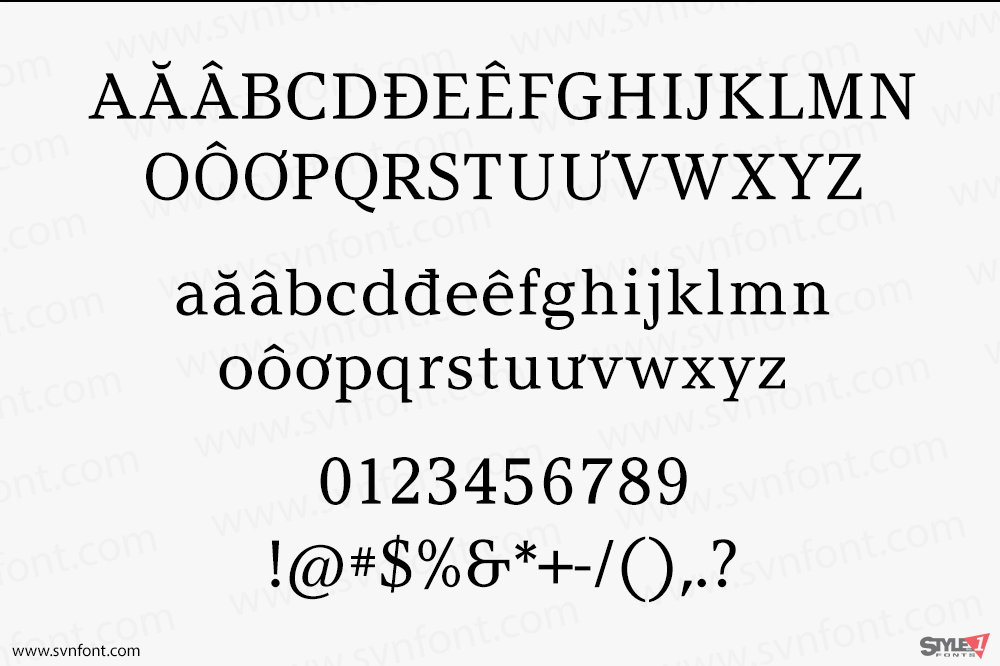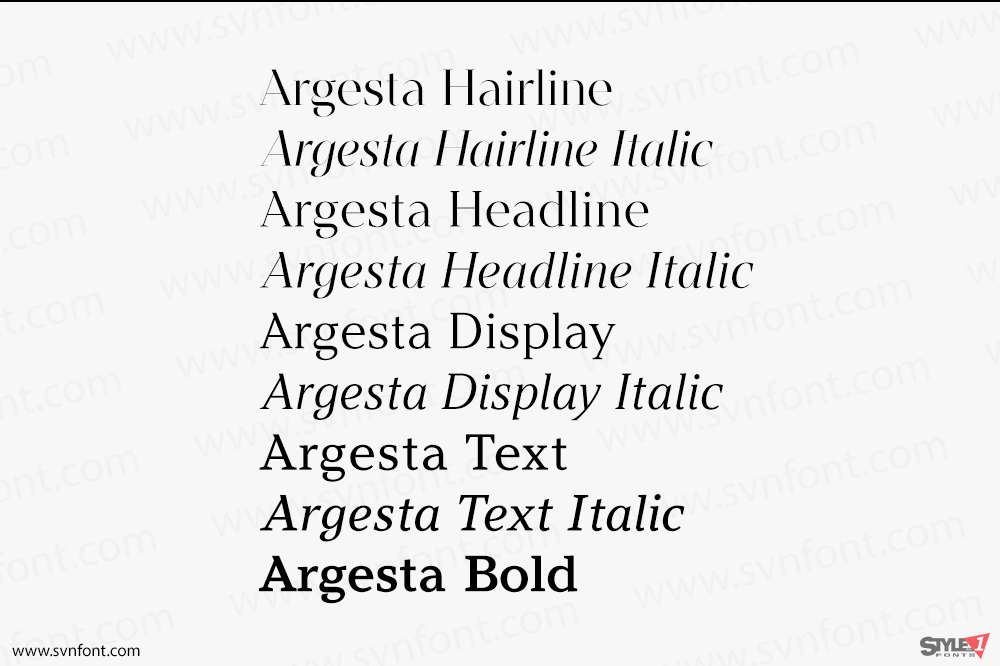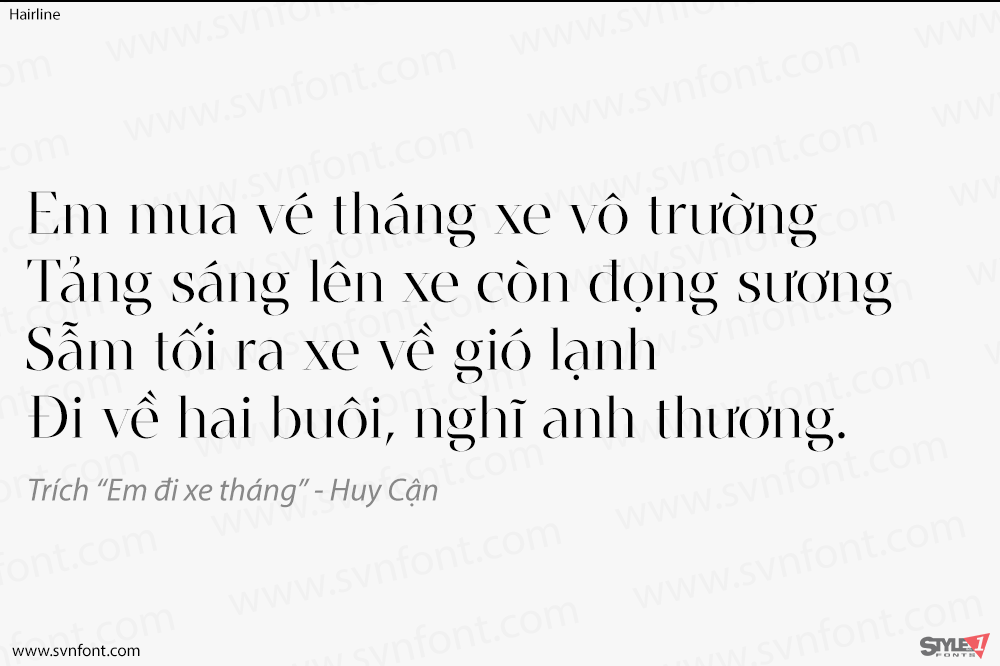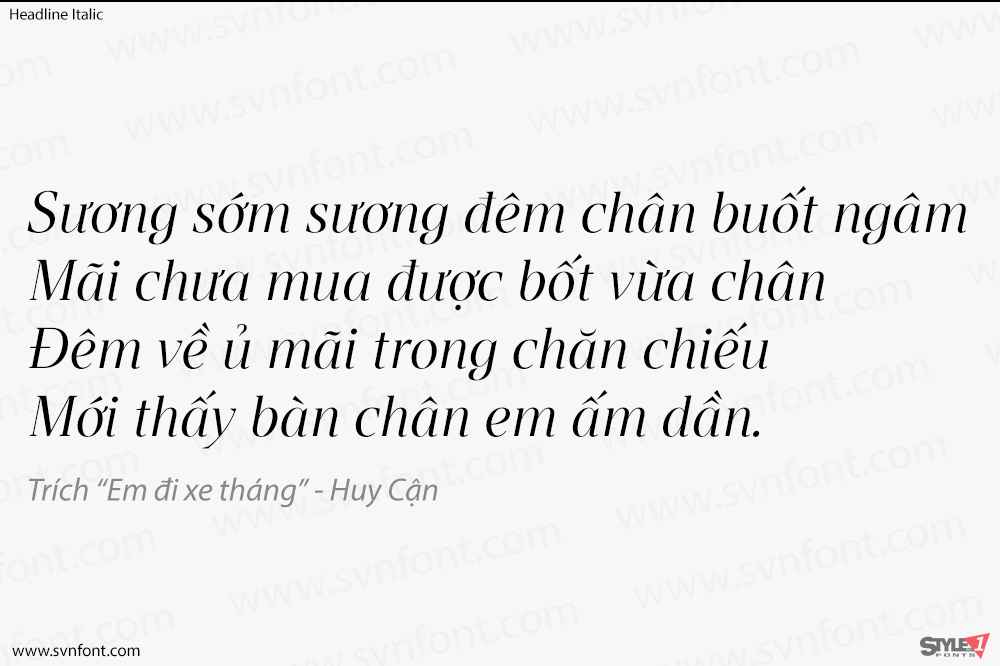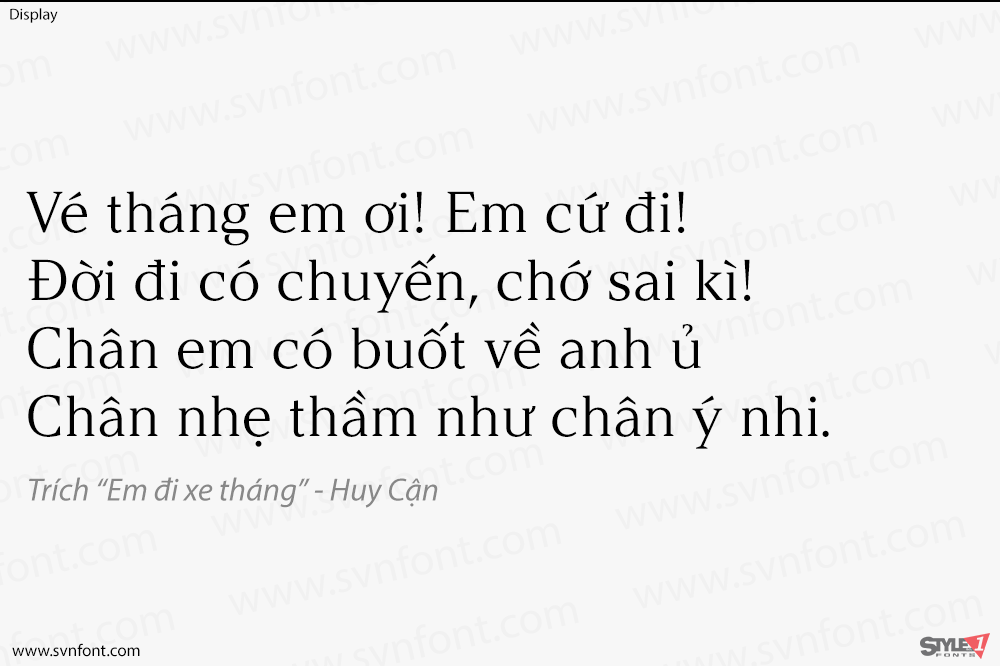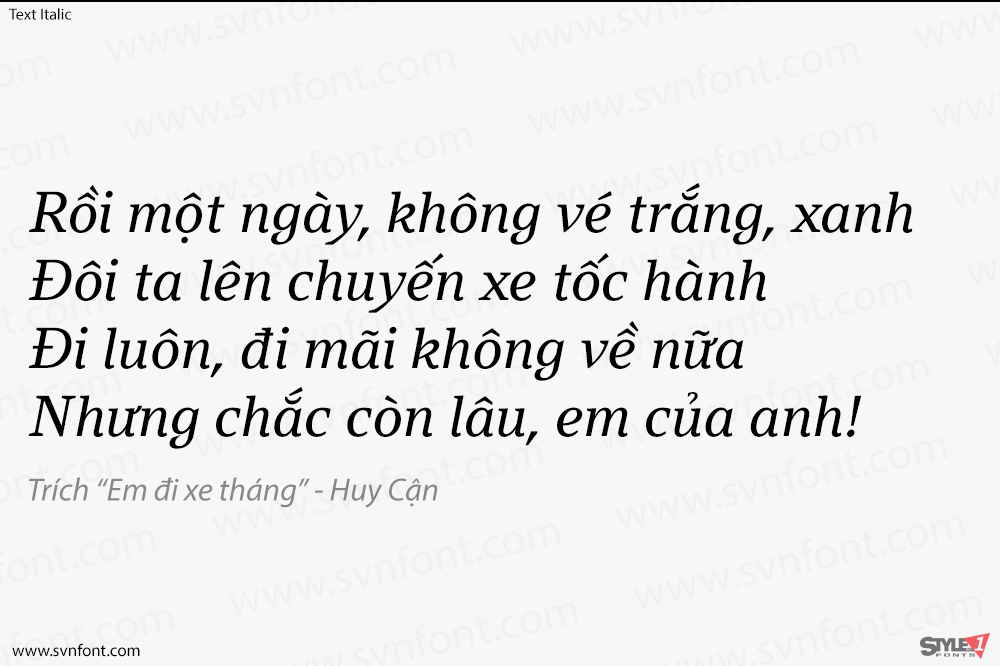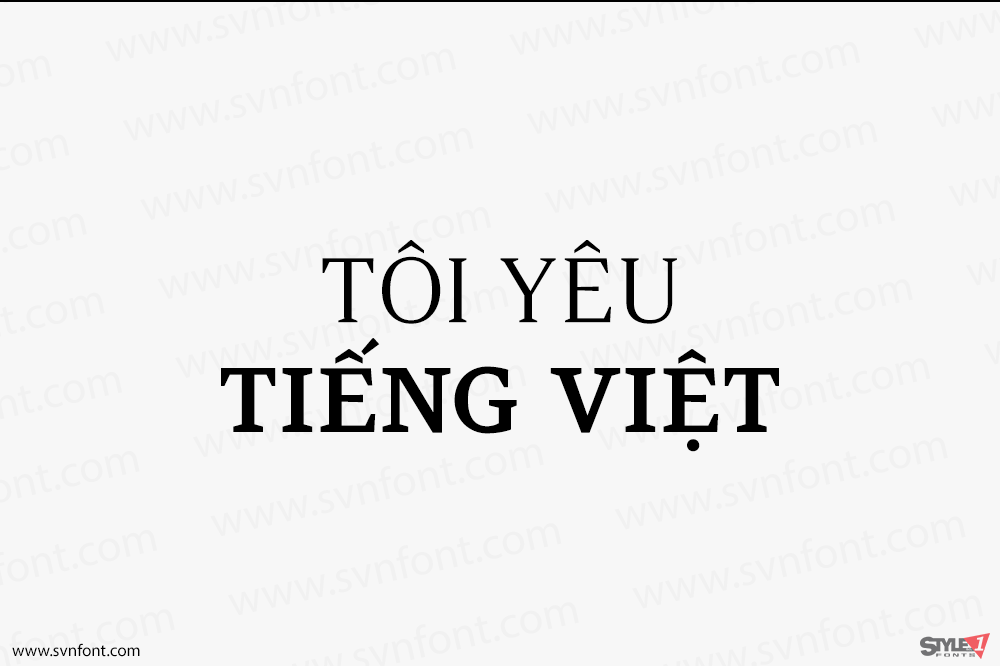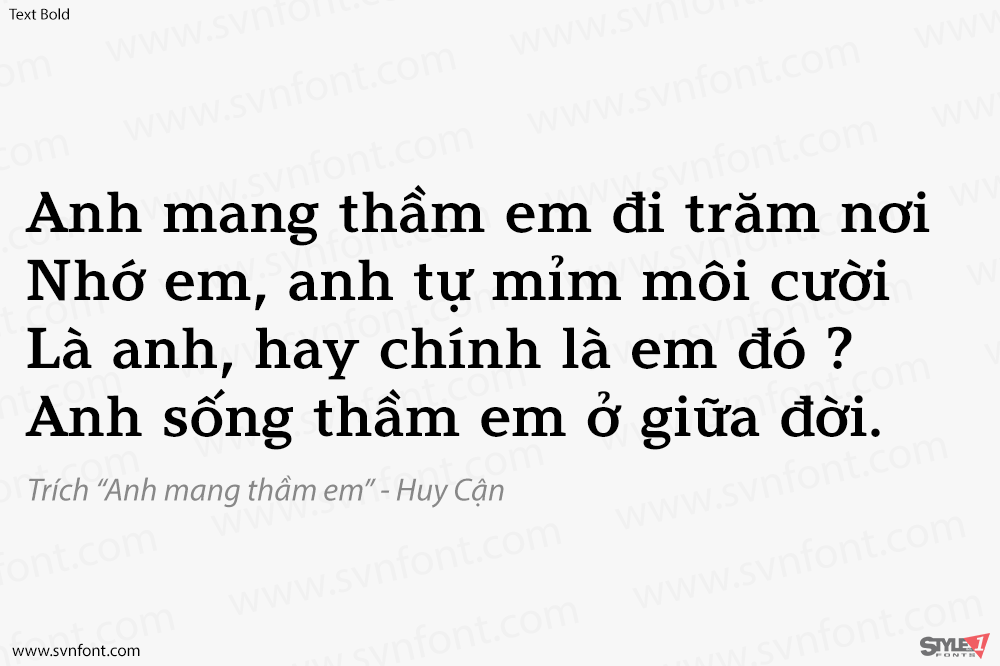
Argesta là một họ font serif tân cổ điển mạnh mẽ với độ tương phản cao. Ý tưởng cho font chữ này có phạm vi tham khảo rộng, từ cổ điển, truyền thống đến hiện đại, khiến nó trở thành kiểu chữ hoàn hảo cho vẻ ngoài tinh tế, hiện đại và thanh lịch. Về mặt phong cách, Argesta được truyền cảm hứng trực tiếp từ thời trang cao cấp (haute couture) và rất phù hợp cho các nhận diện thương hiệu sang trọng, thiết kế tạp chí, hoặc thiết kế bao bì sản phẩm cao cấp.
Nhà thiết kế: atipo foundry
Nhà phát hành: atipo foundry